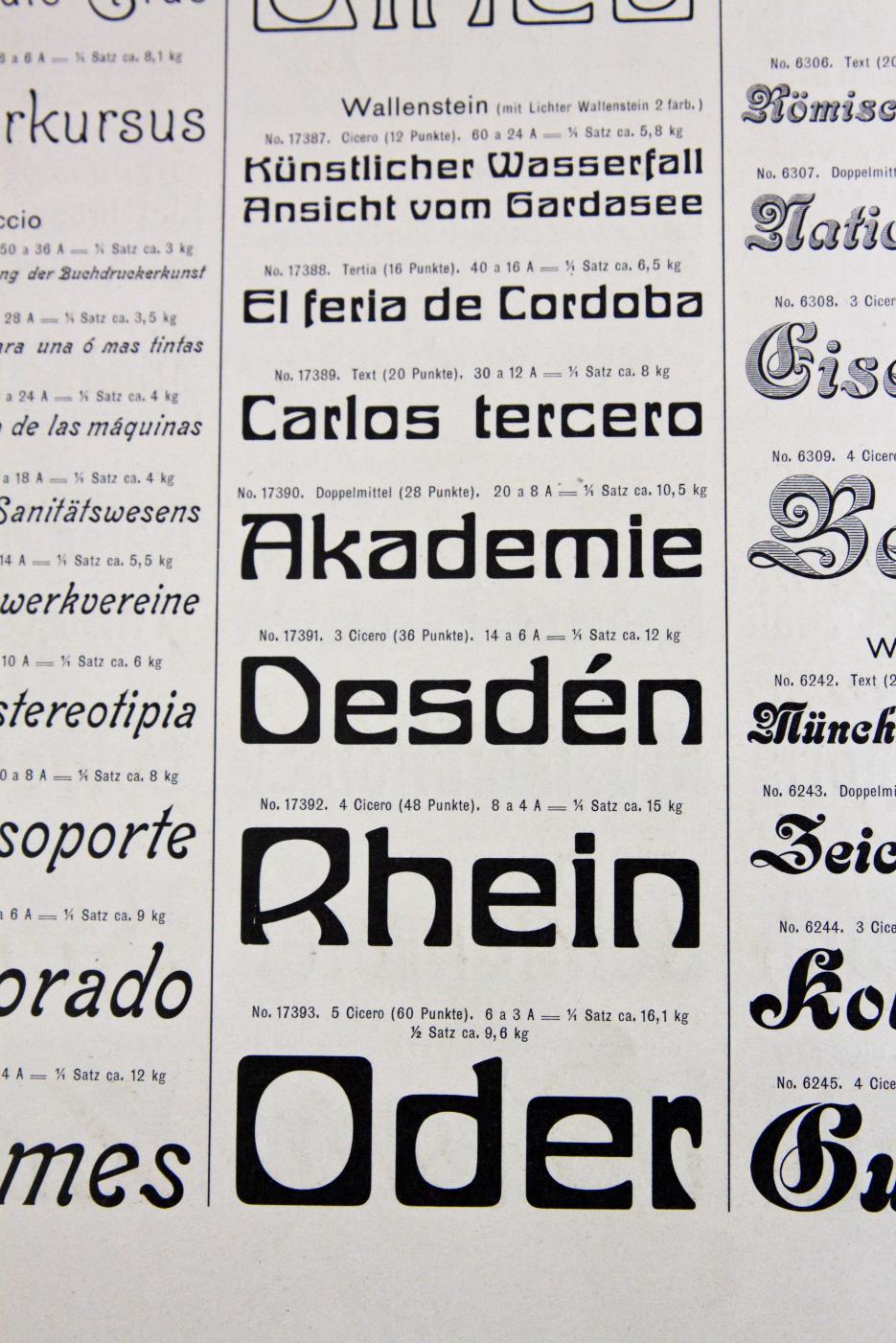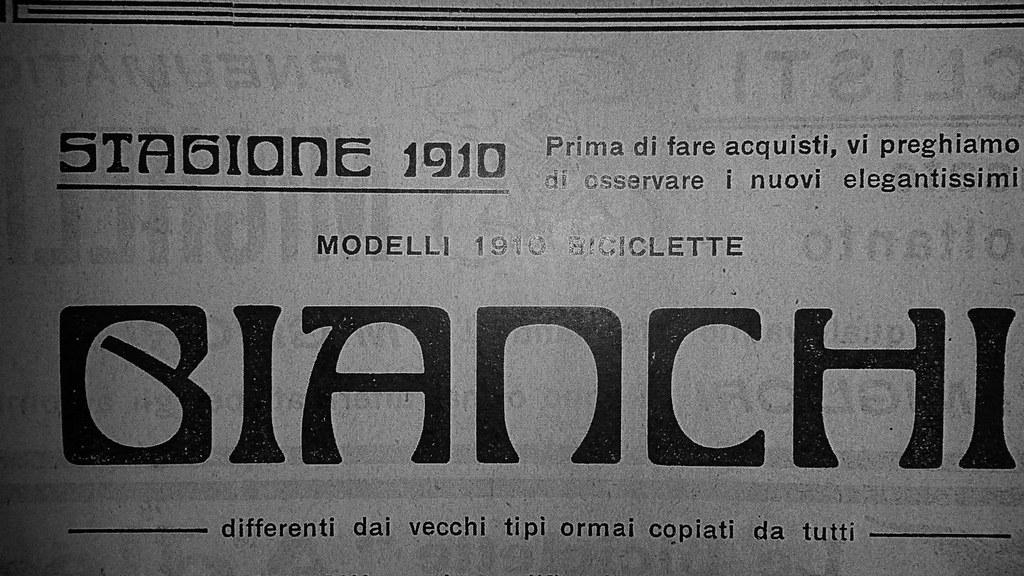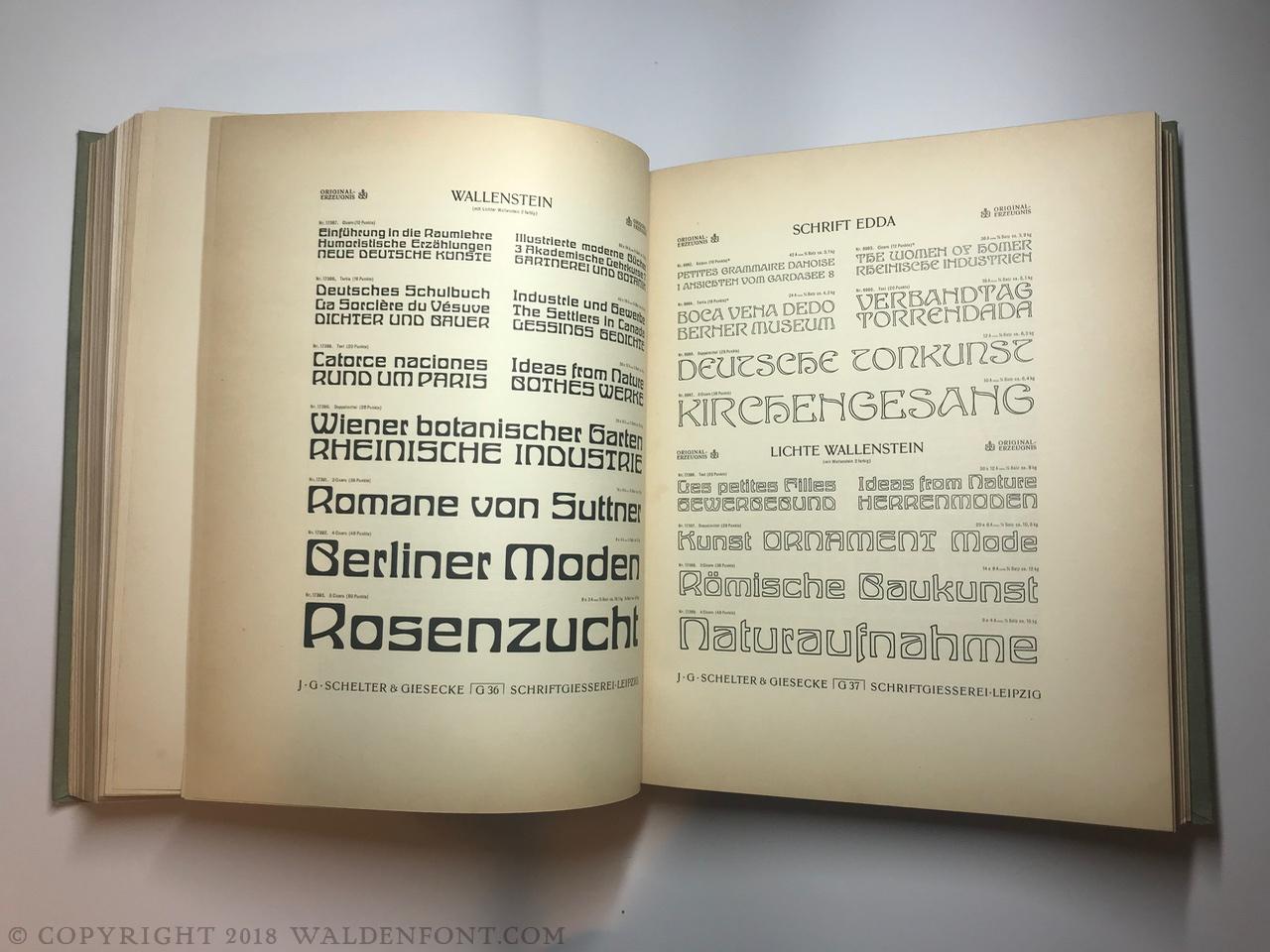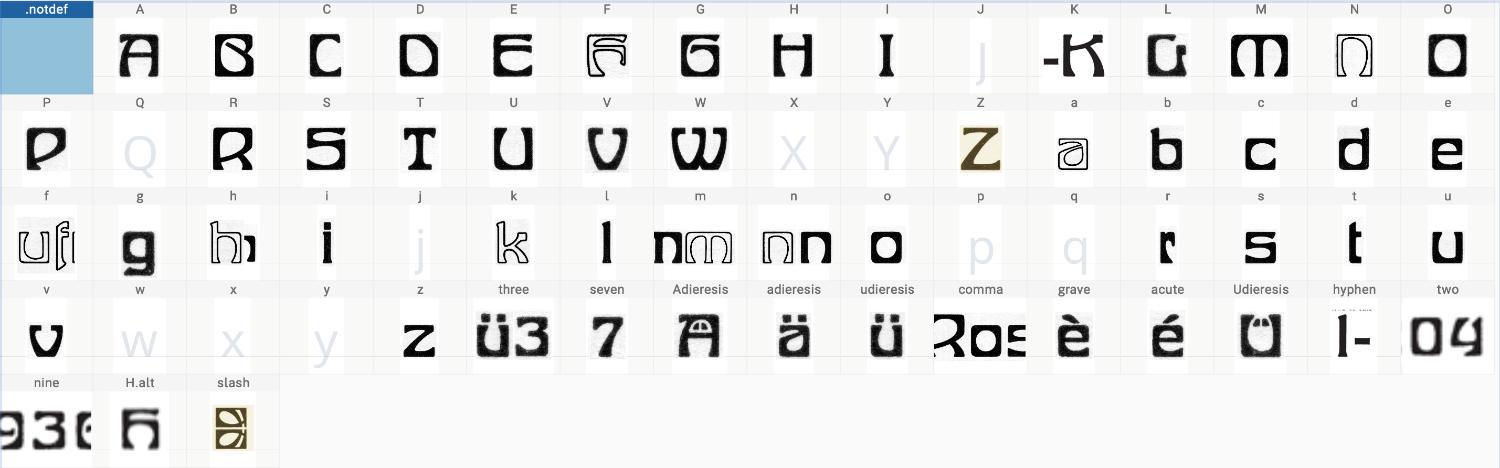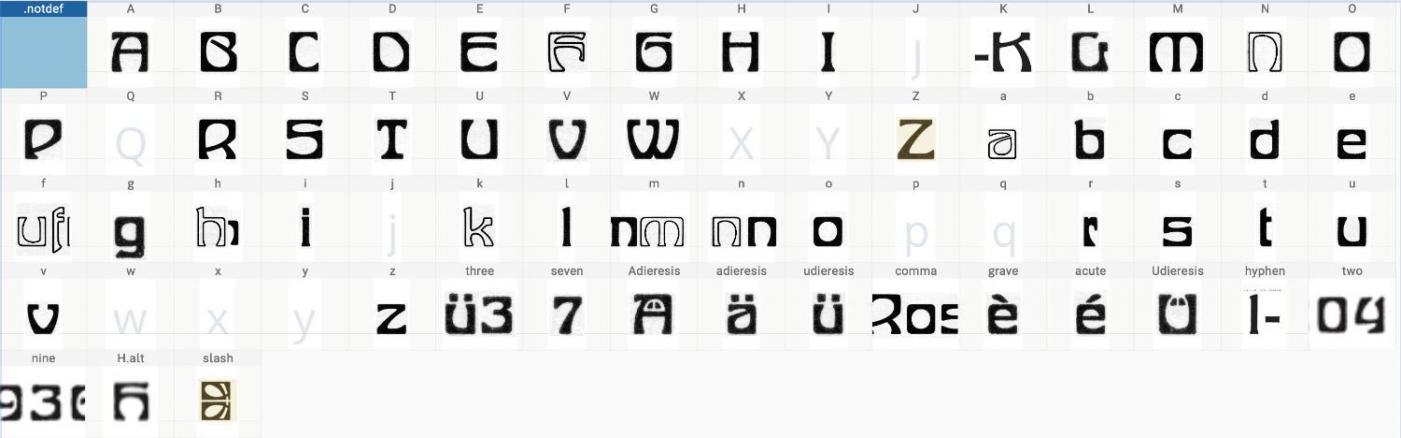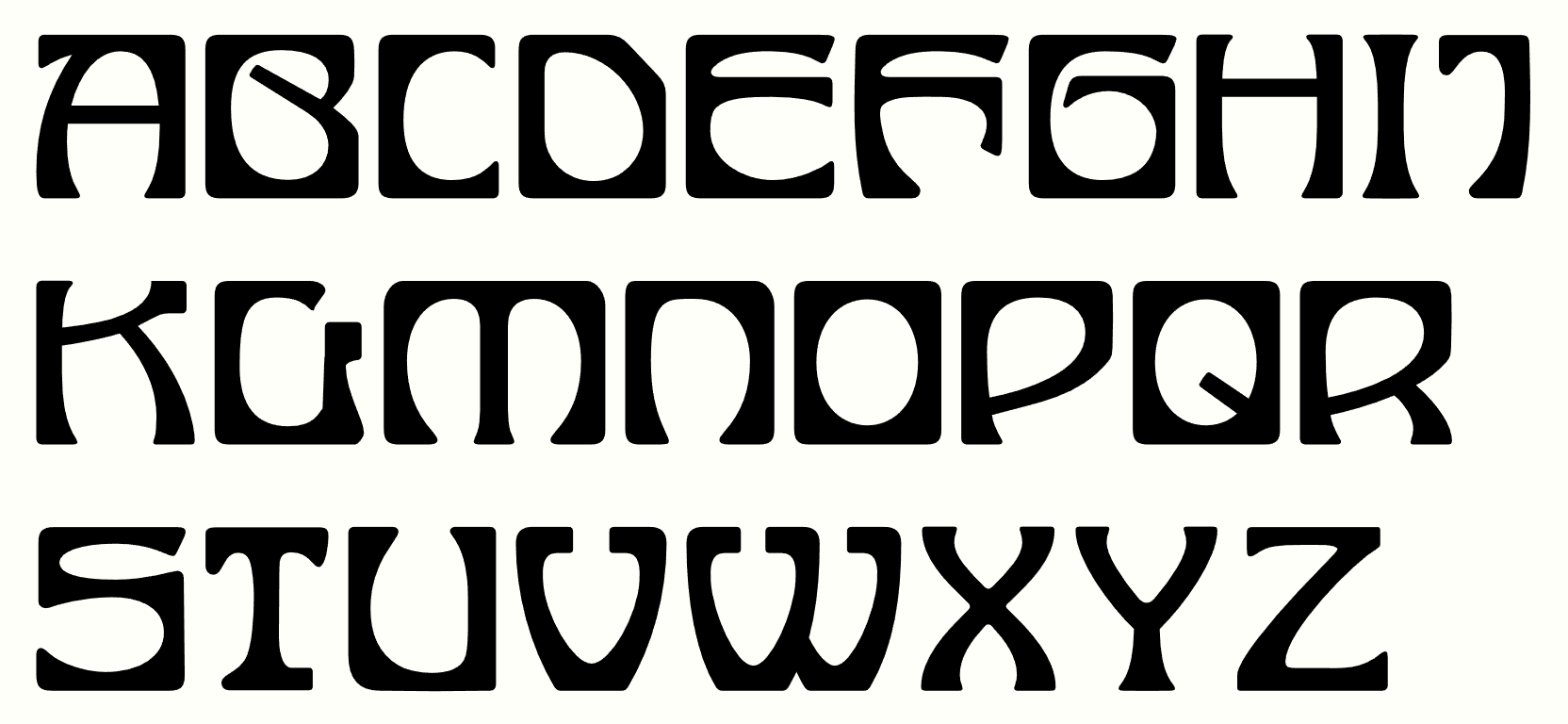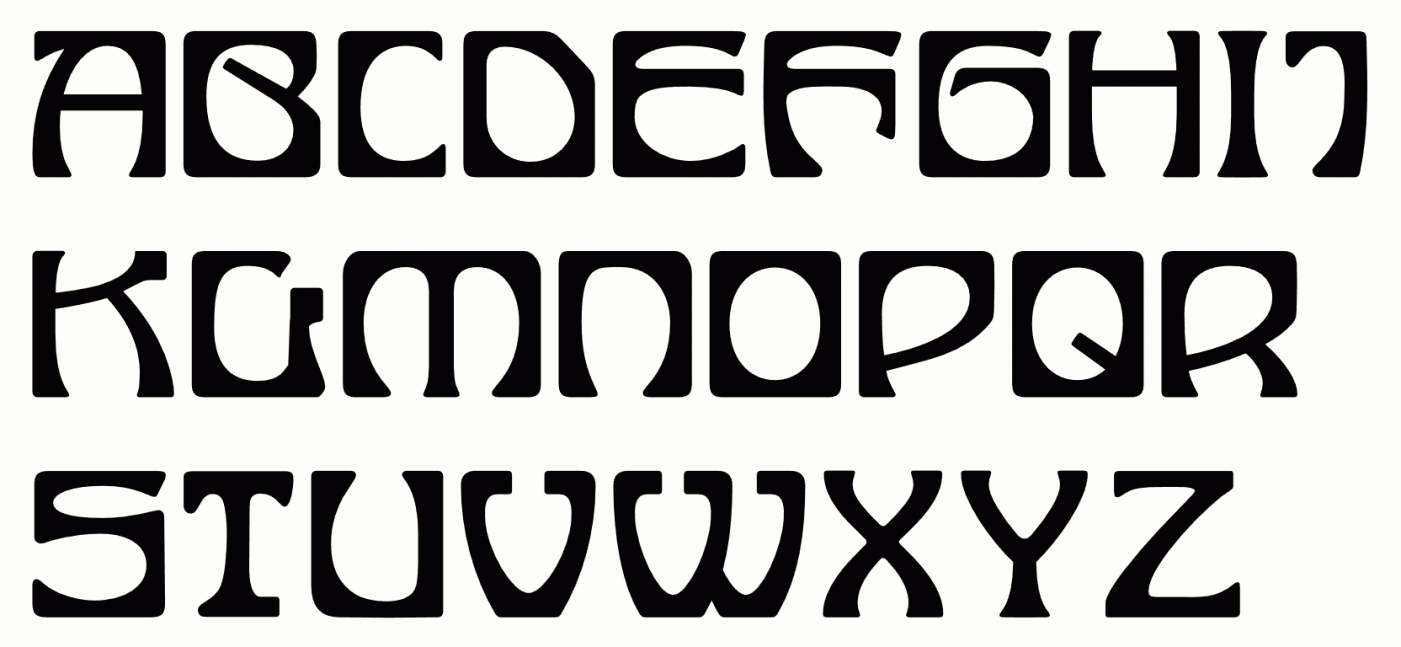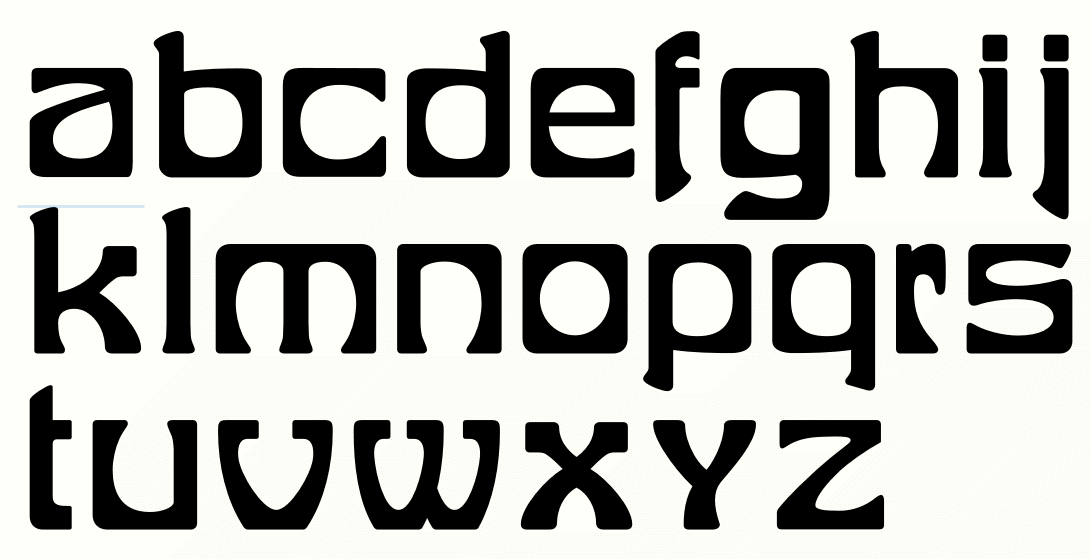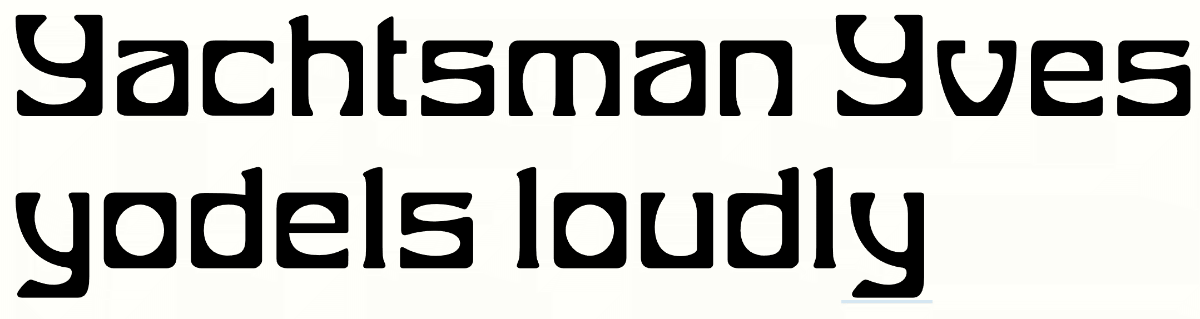
Jugendstil, die Neunte: Wallenstein
...denn Spaß muß sein...
Eine weitere Kreation von Heinz Keune aus dem Jahr 1904. Sie ähnelt der Wittelsbach, besticht aber durch ihr gedrungen- quadratisches Aussehen. Ulkig, jedenfalls.
Das folgende stellt mein gesamtes Quellenmaterial dar. Ich würde mich über weitere Proben oder Anwendungsbeispiele der Wallenstein sehr freuen!
Habe noch Weiteres gefunden. Damit ist das Mysterium Z gelöst. Jetzt fehlen nur noch J, Q, X,Y, j,p,q,w,x,y, 1, 5, 8. Da die Wallenstein recht regelmäßig ist, sollte das kein Problem sein. Auch habe ich erfahren, daß lichte und volle Wallenstein zusammen eine schicke Zweifarbenschrift ergeben. Ich bin gespannt, das auszuprobieren!
vor 1 Stunde schrieb Oliver Weiß:
daß lichte und volle Wallenstein zusammen eine schicke Zweifarbenschrift ergeben.
Da bin ich auch sehr gespannt :-P
Wirst du auch den ganzen »Zierrat« digitalisieren?
Ich fänd es ja spannend, damit mal einen Fußballverein auszurüsten. Ihr wisst schon: »Das Runde muss in das Eckige.« Und wenn’s dann noch ein Verein ist, der etwa in dieser Zeit gegründet wurde¹ …
Eine erfrischende, elegante Alternative zu den immer absurderen Trikot-Blockschriften von Adidas und Co. wär das allemal, denke ich.
1. Ich wäre ja für »Eisern Union« (Berlin), deren Vorläufer 1906 gegründet wurde. Und im O lässt sich auch eine Achse/Welle in einem Gehäuse sehen …
vor 7 Stunden schrieb Norbert P:
Wirst du auch den ganzen »Zierrat« digitalisieren
Klar. Leider habe ich nur dieses Titelblatt.
Edit: habe jemanden gefunden, der vielleicht das ganze Heft besitzt. Mal sehen, ob er antwortet...
Vielleicht interessant – so sieht die Sache aus bevor das Zeichnen beginnt. Die Lettern sind alle bitmaps, also Zeichenvorlagen. Ich habe sie alle auf die gleiche Größe gebracht. Sie stammen aber alle von verschiedenen Schnitten der Schrift und  passen deshalb nicht zusammen. Auch weisen alle verschiedene Qualitätsgrade und Verzerrungen auf. Radien und Strichstärken nehme ich vom größten, saubersten Schnitt. Damit baue ich mir eine Sammlung von "Körperteilen", aus denen ich fehlende Buchstaben mit einiger Treffsicherheit rekonstruieren kann.
Interessante Methodik, gab es auch schon in analogen Zeiten. Martin Wilke, den ich noch kennenlernen durfte, hat das bei seiner Wilke Antiqua mit einem Set von Schablonen von Radien, Formteilen von Buchstaben  etc. praktiziert, für die Reinzeichnung der Schrift.
So ähnlich mache ich das mitden "Körperteilen" einer Schrift auch:
Also spielte ich mit den gefühlt 100 Disketten Diskjockey auf dem vor mit stehenden 386SX. Schnell merkte ich, dass es wohl einen nicht unerheblichen Teil meiner Arbeitszeit kosten wird, mich da einzuarbeiten, und ich durch meine anderen Aufgaben auch viel zu oft abgelenkt würde. Also machte ich meinem Chef den Vorschlag, ob ich dieses Einüben nicht auf meinen (bei mir damals noch nicht exidtierenden) privaten PC installieren könnte, um meine Übungsstunden dann lieber daheim und in Ruhe machen zu können. Zu meinem Erstaunen ging er auf diesen Vorschlag ein und stellte mit 4 Packungen Disketten auf den Tisch, und ich bestellte mir auch gleich - damals beo Quelle - einen PC, auch einen 468 SX mit nur 649 kB SD-RAM und 52MB Festplatte, dazu MS-DOS 4.1 und Windows 3.1.
Ein paar Tage später hatte ich dann so meine erste richtige Software zuhause.
2 Monate späterstand mein Chef wieder in meinem Büro, "Corel hat mich angeschrieben, die haben ein Fehler-Upgrade bereitgestellt, bitte kopieren Sie von ihrem Rechner aus dem Corel-Installationsverzeichnis die Datei 4711.dat und schicken die Diskette nach Irland an diese Adresse hier."
Also kopierte ich die gewünschte Tatei auch von meinem Rechner und schrieb nach Irland mit der Bitte, mir das Update zuzusenden. Zu meiner größten Überraschung kam dann nicht ein Umschlag mit ein paar Fehler-Korrektur-Disketten, sondern ein recht großes Paket mit der kompletten Version 1.10, mit eigener Seriennummer, Registrierung auf micht und dem Ausweis für die Upgrade-Berechtigung für die nächsten Versionen zum jeweils viertel Preis der Vollversion, die ich hiermit jetzt legal hatte. So hatten sie mich dann als Kunde eingefangen...
Gestern Abend hielt ich geistige Zwiesprache mit Herrn Keune. Nach einer Weile ging mir ein Kronleuchter auf: Mensch, der basiert seine Schriften doch überhaupt nicht auf Antiqua - das ist alles Fraktur! (naja, fast alles). Y/y gleich nochmal gemacht, und schon paßt es viel besser. y ist noch ein wenig luftig, und Y vielleicht zu rund, aber so ähnlich wird das wohl ausgesehen haben
Noch ein Fundstück: